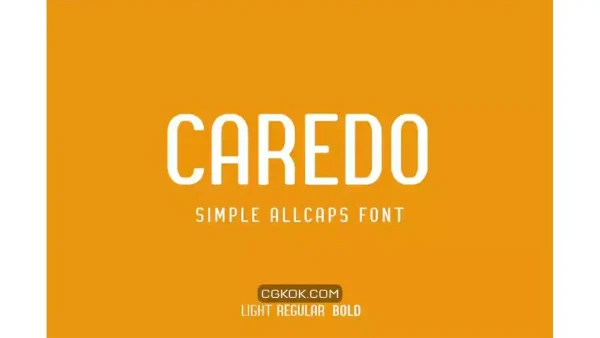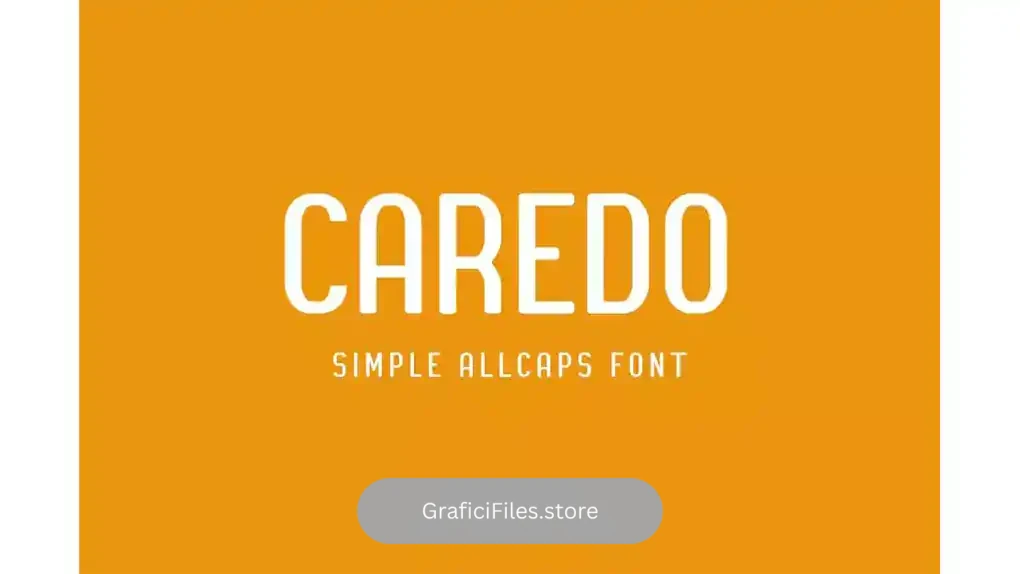
دانلود فونت انگلیسی ساده Caredo – Simple font
فونت انگلیسی ساده Caredo – Simple font : این مجموعه شامل یک فونت انگلیسی ساده است که برای عنوان مجله، تیتر، روزنامه، اداری، پوستر، جلد کتاب، لوگو، بنر و غیره مناسب میباشد.
مشخصات دانلود فونت انگلیسی ساده Caredo – Simple font :
• عنوان مجموعه: Caredo – Simple font
• سبک: Sans-Serif
• فضا بین حروف: معمولی
• اندازه بهینه: تمامی سایز ها